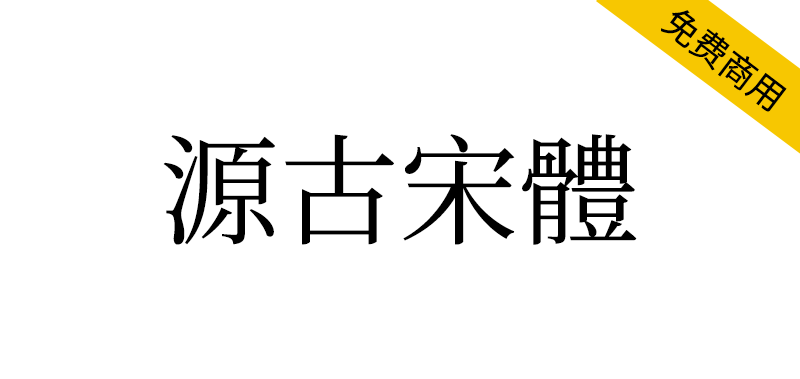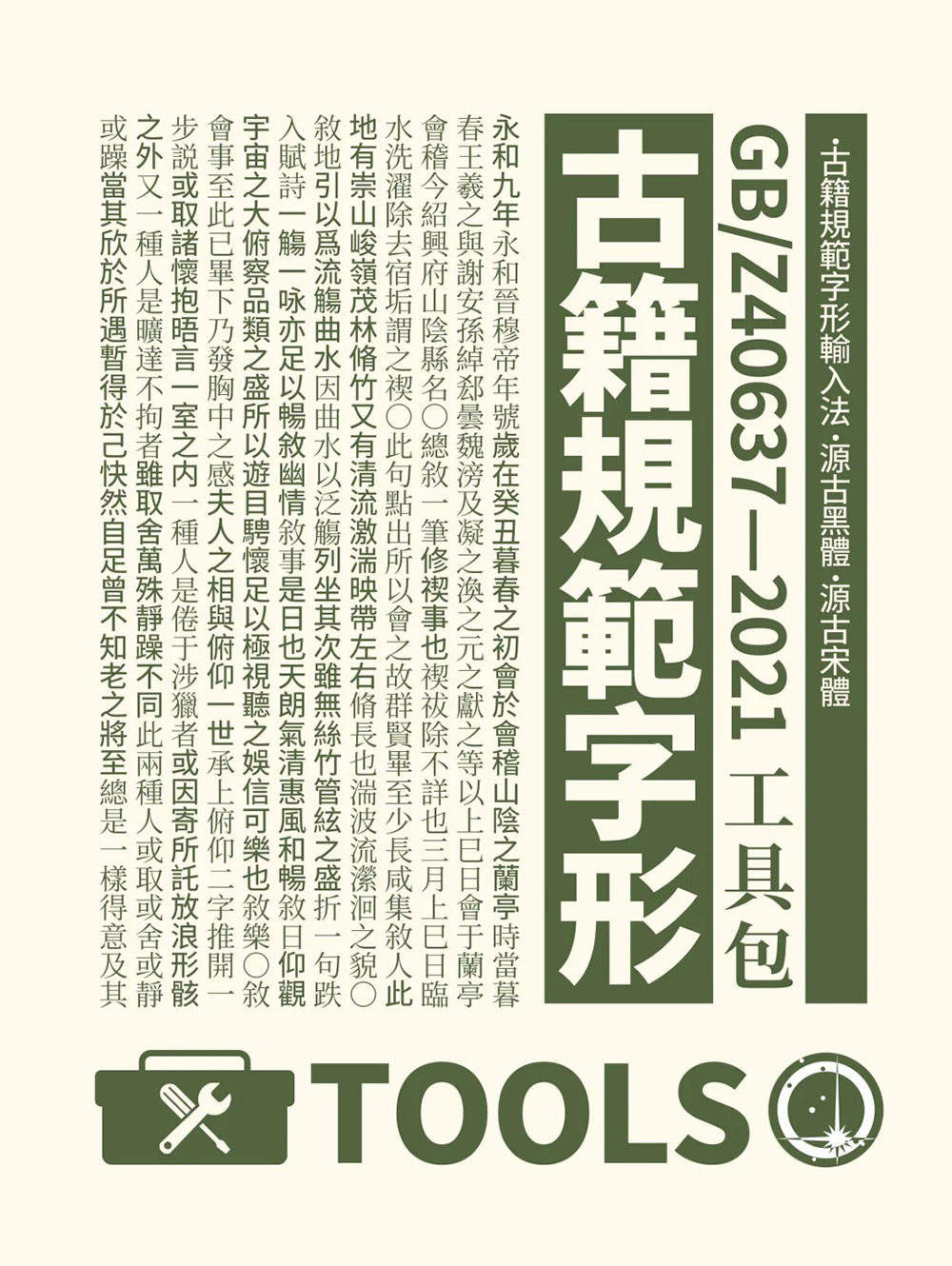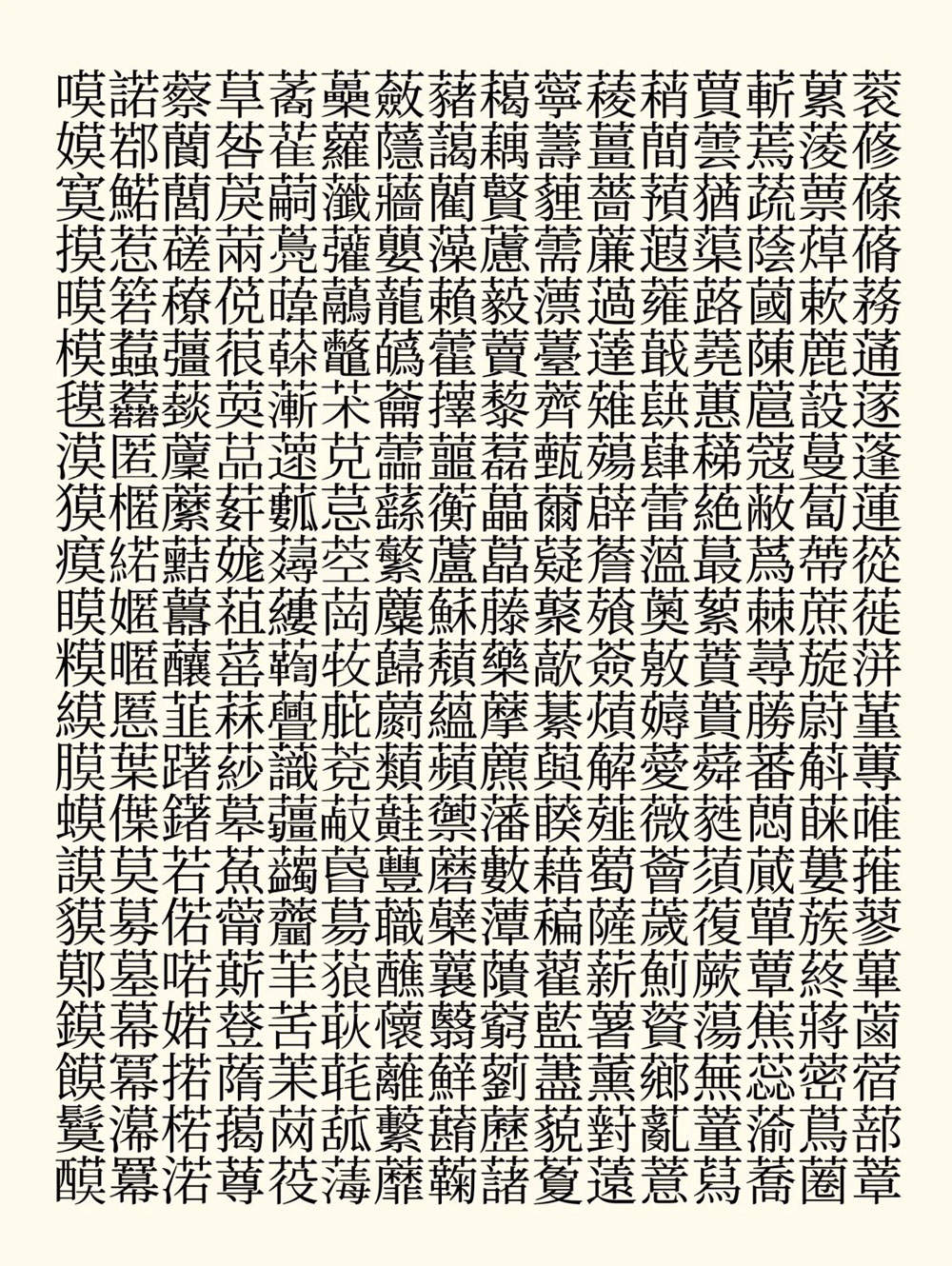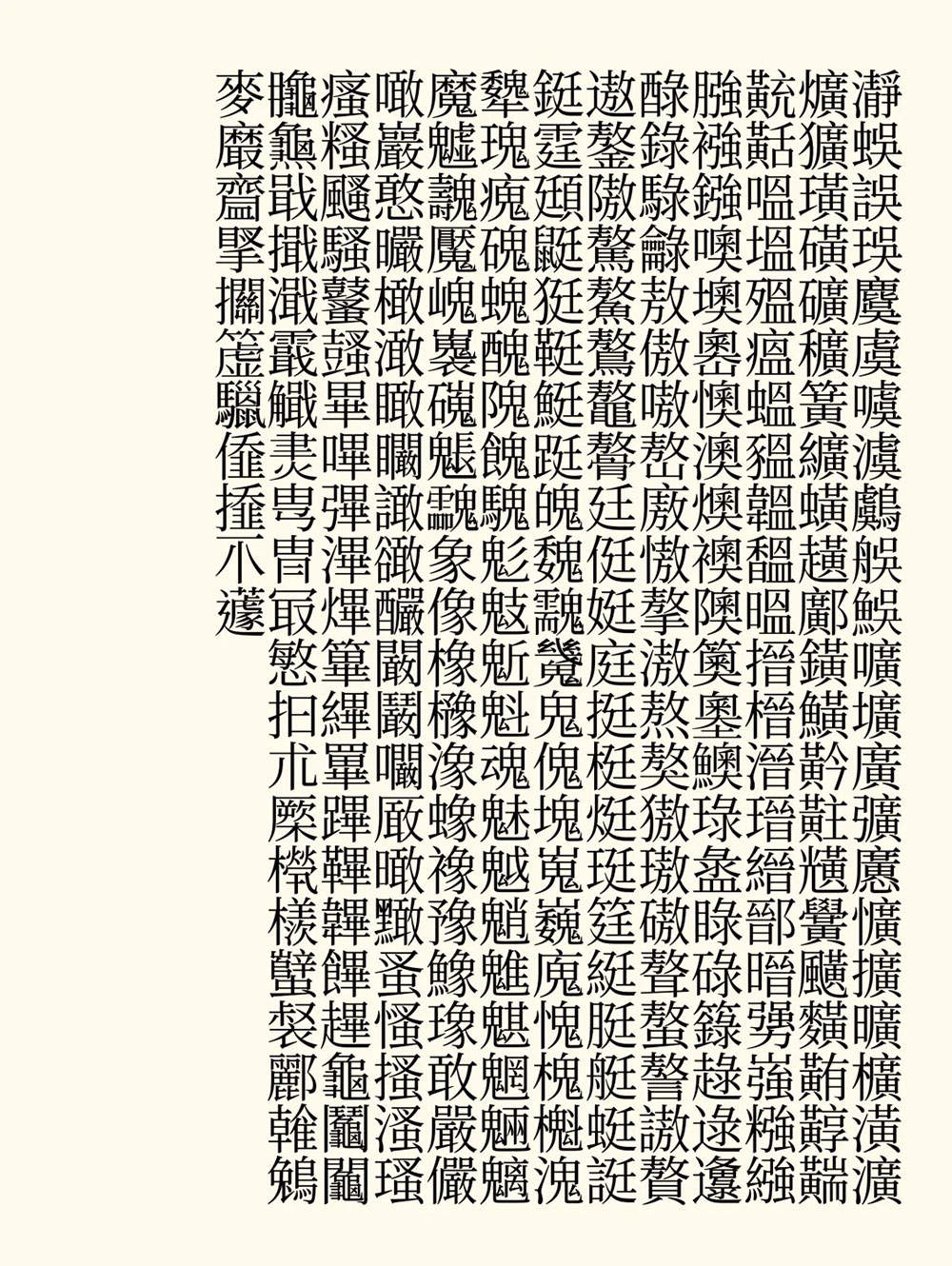
根据《古籍印刷通用字规范字形表》(简称“古籍表”)校改的思源黑∥宋体,以及配套输入法。《古籍表》作为大陆地区最新的繁体字字形标准,却迟迟没有相关的配套字体和输入法可用。于是就想着先自己手搓了一个(也为以后炼丹做个准备),希望能抛砖引玉,让很多人了解并使用起来。
古籍印刷通用字规范字形表:这个《古籍表》是在北京师范大学资深教授王宁先生的带领下,以汉字学科学理论为指导,以我国第一部大型辞书《辞源》所收文言词汇为切入点,在对海量古籍数字化资源进行统计测查基础上,确立严谨、科学的规范原则和验证条例,按照定字数、定主形、定笔数、定字音、定编码的“五定”目标,历时6年研制完成的。这是新中国成立以来对传世古籍印刷字的第一次整理规范。
该标准规定了古籍印刷通用字收字和宋体字形规范原则,给出了14250个古籍印刷通用字的字形、字音以及在国际编码字符集ISO/IEC 10646中的码位,适用于传世古籍的印刷出版,以及现代书刊的繁体版印刷。该标准的发布实施,对于推动语言文字规范化标准化信息化,传承弘扬中华优秀传统文化,建设社会主义文化强国都具有重要促进作用。
用不太准确但最容易理解的话说:此表是我国大陆地区第一个正式的繁体字规范。我愿称之为真·国标繁体。
1、首先是输入法,我折腾了两个rime输入法方案。
一个是基于小狼毫自带的朙月拼音修改的朙月拼音-古籍规范版,朙月拼音本来就是用的繁体词库,转换起来很方便,一个字表就可以搞定。
一个是基于白霜词库修改的白霜拼音,这个是一个很强大的多功能简体词库,支持各种符号、emoji输入,还可以拆字输入,对于用惯了微软拼音拆字功能的人来说很亲切。而因为是简体词库,所以除了转换字表,还要配一个词表,以处理那些一简对多繁的字。
而转换用的字、词表的基础都来自于github上的古籍表opencc项目,然后我根据自己使用时觉得不舒服的地方,调整了一些过于古旧的用字(才、吃、翫之类的)的出现优先级,以防默认出词面貌看起来太老古董。
2、然后是字体,这我老本行了,可谓轻车熟路。这次我一下做了两种,一种黑体一种宋体。
源古黑体基于思源黑体改造,扩B区的字取自遍黑体;源古宋体基于思源宋体改造,扩B区的字取自文津宋体。
得益于思源丰富的地区字形,拆拆凑凑很方便就可以改出一个古籍表版本。而关于那些部件不统一的字,我有选择性地擅自进行了统一。
然后黑体和宋体各提供了两个版本,一个是仅包含古籍表表内字的纯古籍表版,一个是把古籍表外的——思源本来有的那些字一股脑放进去的“F”版本(当然这些表外字就没有按古籍表规范修改,保持思源原样)。
各位可以按需选用。日常看书写东西可以用F版,确保不缺字。如果要作为做字体的参考或者炼丹的底子,就可以用纯古籍表版,以免被表外字误导。(没错,其实这次弄这俩字体,本来就是作为炼丹工具性质的)
除了这些“鱼”,我还准备了一些“渔”:我把我做字体时用到的、总结的各种字表都放在了包里。各位做字同仁可对照这些表,把自己的国标字体改造成古籍表标准。